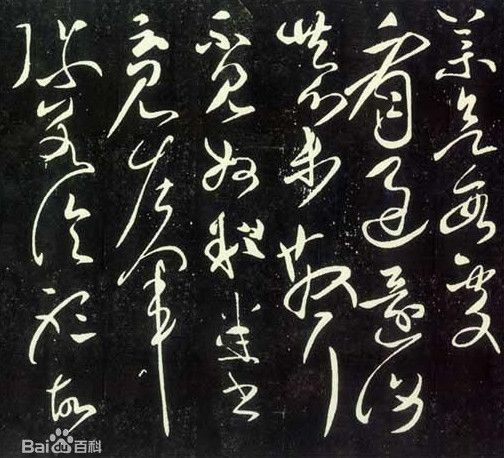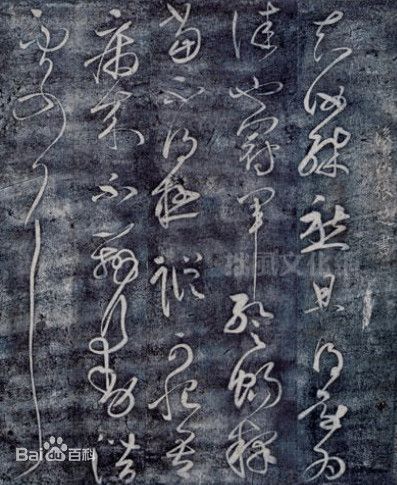
张芝简介_书法四贤之一_张芝草书_张芝书法作品价值
张芝,东汉书法家。擅长草书中的章草,将古代当时字字区别、笔画分离的草法,改为上下牵连富于变化的新写法,富有独创性,在当时影响很大,有草圣之称。张芝与钟繇、王羲之和王献之并称书法四贤。史上说的草书“二张”即指张芝和张旭。
张芝,字伯英,勤学好古,淡于仕进。朝廷以有道征不就,时人尊称自为“张有道”。善章草,后脱去旧习,省减章草点画、波桀,成为今草, 张怀瓘《书断》卷中列张芝章草、草书为神品。
草圣张芝作品
张芝从民间和杜度、崔瑗、崔实那里汲取草书艺术精华,独创“一笔书”,亦即所谓“大草”,使草书得以从章草的窠臼中脱身而出,从此使中国书法进入了一个无拘无束,汪洋恣肆的阔大空间,从而使书法家的艺术个性得到彻底的解放。
“书圣”王羲之最推崇的前辈书家有两个:一个是魏的钟繇,一人是东汉的张芝。他说:
吾书比之钟、张,钟当抗行,或谓过之;张草犹当雁行。然张精熟,池水尽墨,假令余耽之若此,未必谢之。
连王羲之都自叹弗如,可见张芝对书法的热爱程度。
张芝的草书给中国书法艺术带来了无与伦比的生机,一时名噪天下,学者如云。王羲之对张芝推崇备至,师法多年,始终认为自己的草书不及张芝。
书法四贤张芝作品欣赏
张芝虽以杜度、崔瑗为师,但后来居上,“超前绝后、独步无双”。唐开元时著名书法家和评论家张怀瓘,在其名著《书断》这部中国书法史上杰出的专著中有数百字比较详细地论述了张芝,其他历代书法家大都引用和认同张怀瓘等人的论述,张芝草圣的地位自此就赫然屹立于华夏书坛之上,永远闪耀着灿烂的光芒。
张芝的草书影响了整个中国书法的发展,为书坛带来了无与伦比的生机。被誉为中国书圣的王羲之,中年就师承张芝,推崇张芝,自认为草书不如张芝。狂草大师怀素也自谓草书得于"二张"(张芝、张旭)。草书大家孙过庭在其《书谱》中也多次提到他一生是将张芝的草书作为蓝本的,称“张芝草圣,此乃专精一体,以致绝伦”。